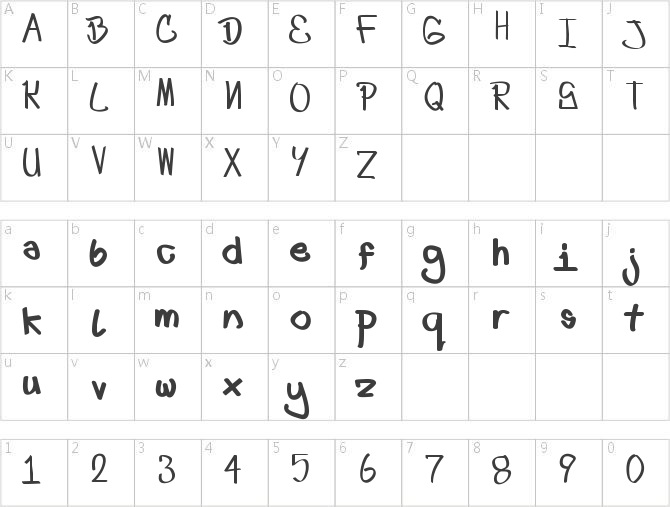
Craze One's first font 詳情頁
Craze One's first font字體字庫是一款讓人賞心悅目、百看不厭的英文字體,適合各類廣告和產(chǎn)品包裝設(shè)計應(yīng)用,字體大小0.05MB,格式為ttf字體,上傳用戶是浪跡天涯,作者/版權(quán)方為未知